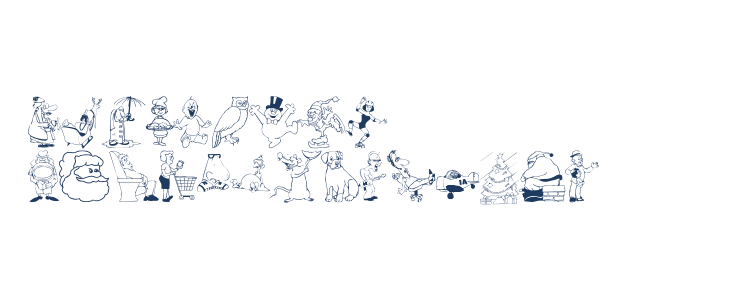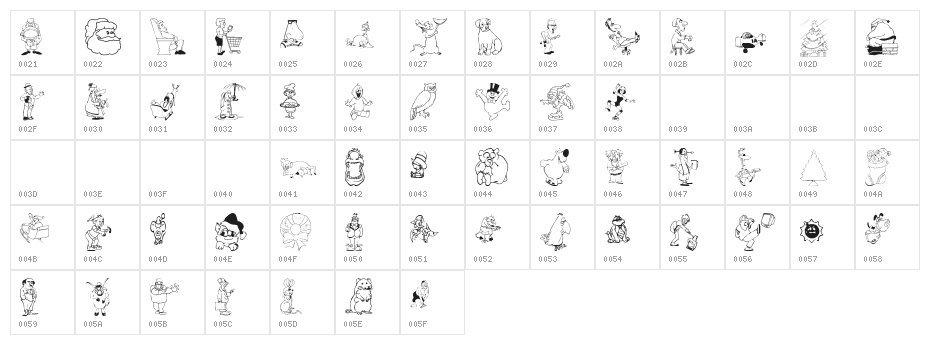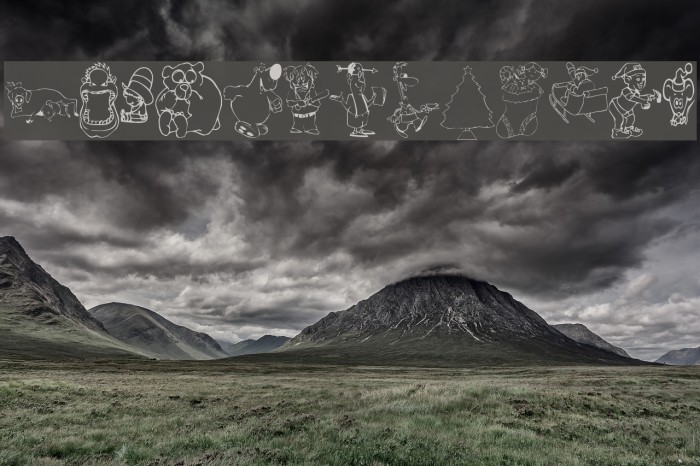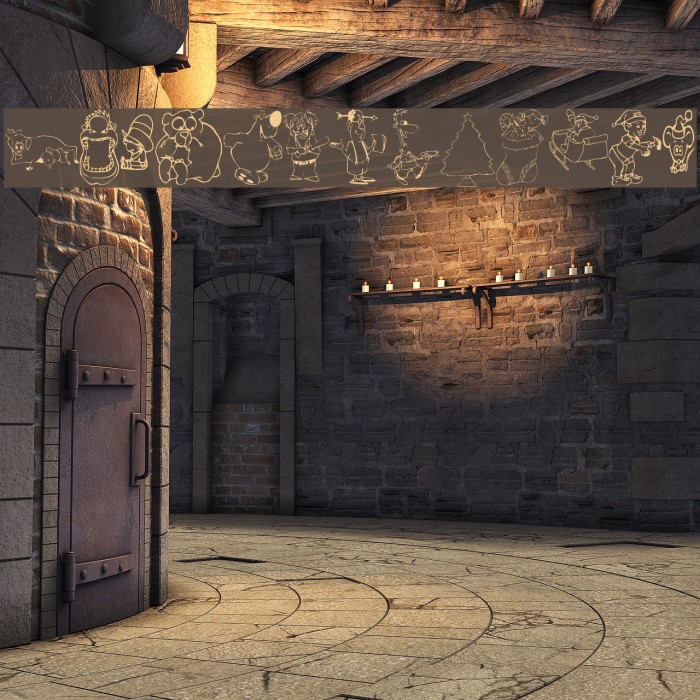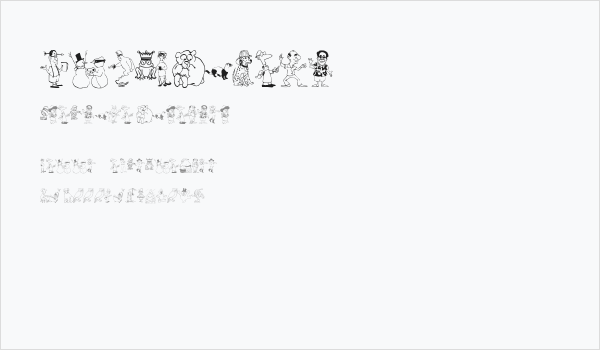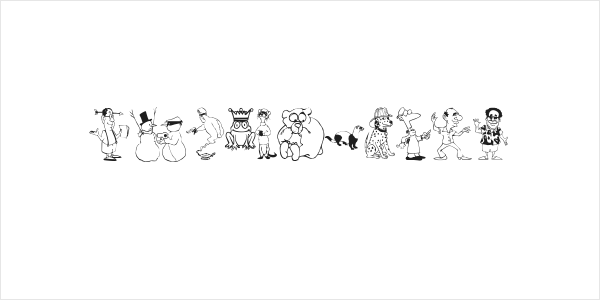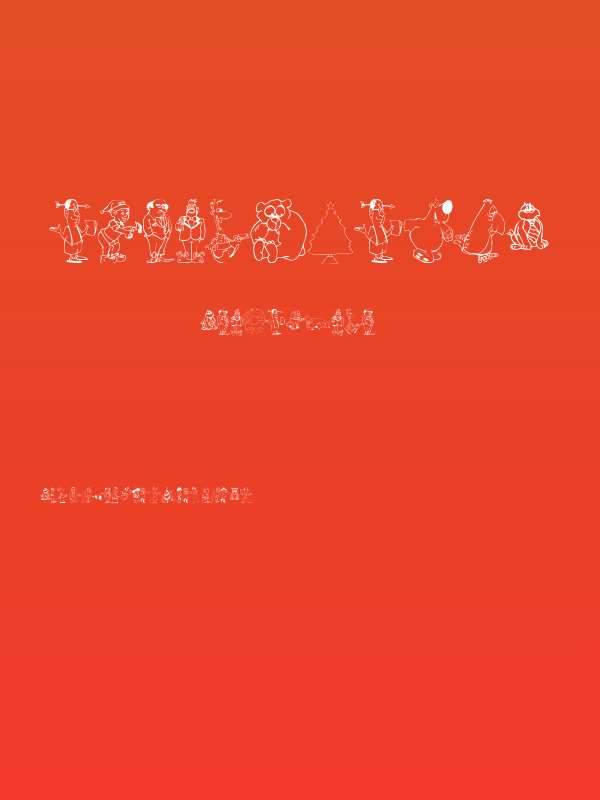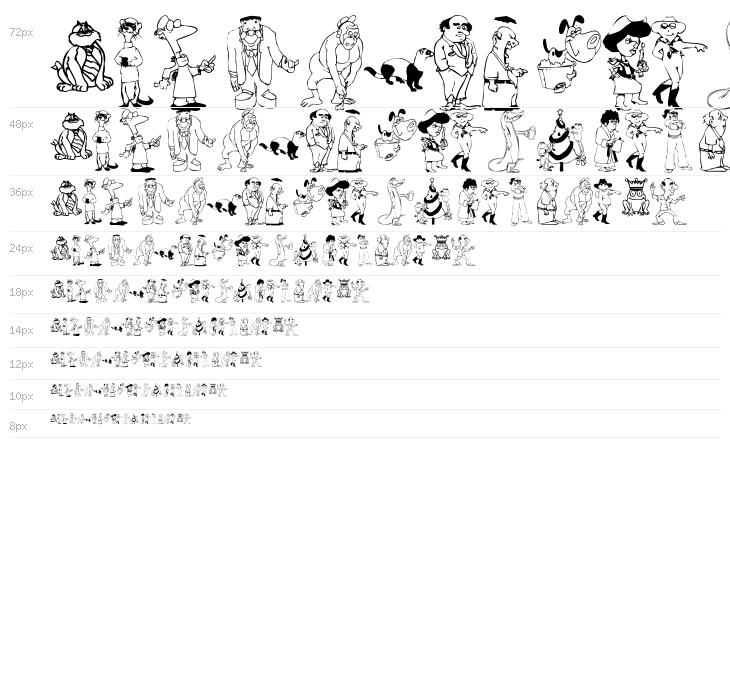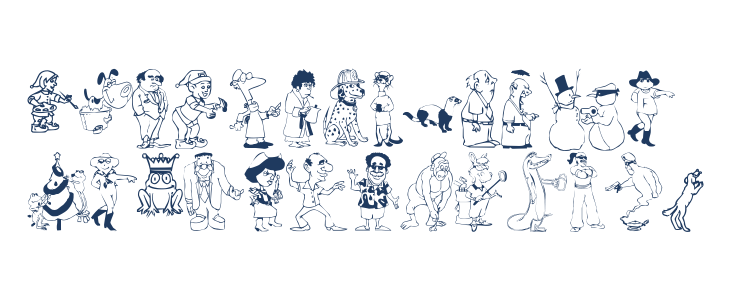
GlyphDigest Font
✎ Cartoon
| Stile generale | Whimsical, Playful, Cartoonish |
| Caso d'uso | Decorative titles, illustrations, novelty projects, branding for kids' products. |
| Progetti proposti | Children's books, comic strips, greeting cards, educational materials, playful branding, party invitations. |